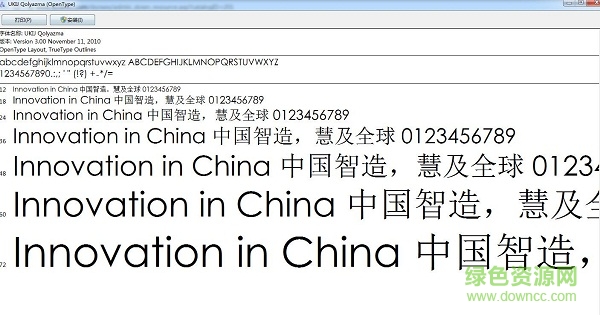
ukijqolyazma字體是一款無(wú)襯線字體,筆畫(huà)纖細(xì)勻稱,可讀性非常好,適合用作藝術(shù)字、雜志封面以及平面設(shè)計(jì)的字體,有需要者歡迎免費(fèi)下載!
1.因?yàn)闊o(wú)襯線字體通常有藝術(shù)性,因此在顯示器上顯示通常比較賞心悅目;
2.英文報(bào)紙的標(biāo)題大多是使用無(wú)襯線的字體;報(bào)紙的頭版頭條標(biāo)題一般都會(huì)是各種粗細(xì)一致的綜藝體或者是中黑體;
3.凡是使用無(wú)襯線字體的,必須保證其在正文內(nèi)容中的可讀性。